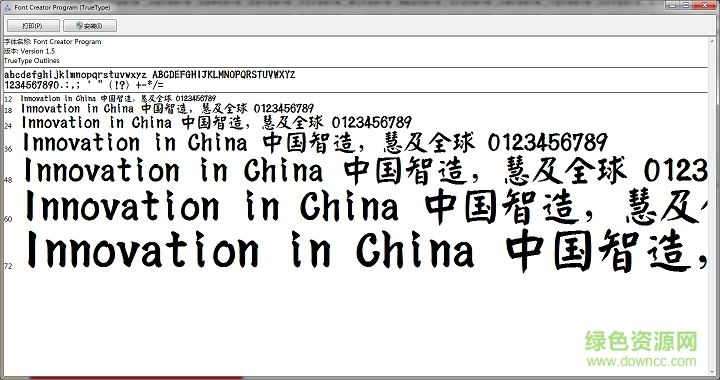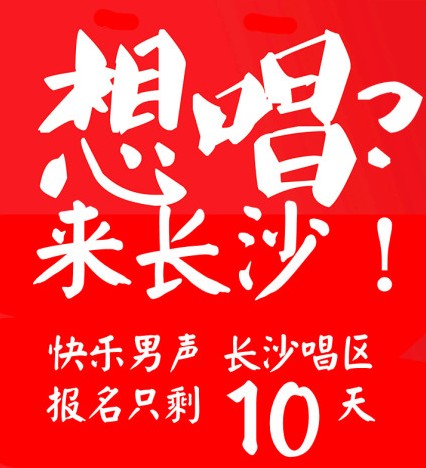
文鼎大顏楷簡(jiǎn)體
文鼎大顏楷簡(jiǎn)體是一款很受歡迎的字體,因?yàn)檫@是2013快樂(lè)男聲宣傳片使用的字體,這款字體是真實(shí)可用的,下載后不會(huì)出現(xiàn)不是有效字體文件提示,所以大家放心下載使用吧!
文鼎大顏楷字體給人感覺(jué)既端莊又厚重,還有飄逸感,非常有個(gè)性的字體啊!